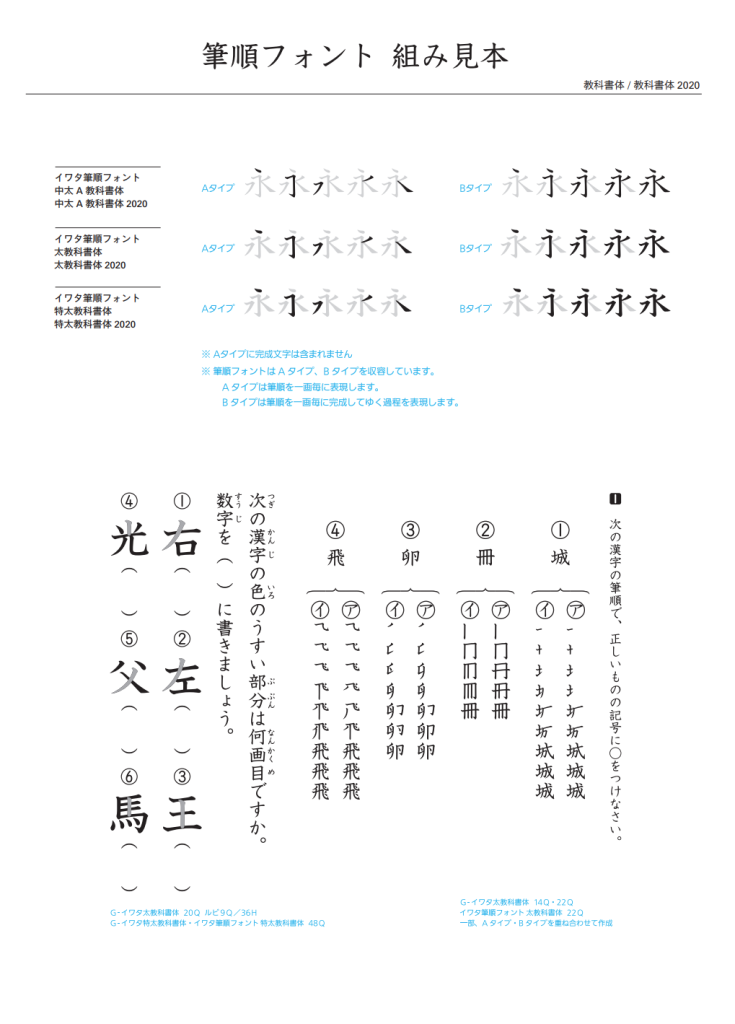
筆順フォント 教科書体2020
イワタ筆順フォント 中太A教科書体2020 Aタイプ
イワタ筆順フォント 中太A教科書体2020 Bタイプ
イワタ筆順フォント 太教科書体2020 Aタイプ
イワタ筆順フォント 太教科書体2020 Bタイプ
イワタ筆順フォント 特太教科書体2020 Aタイプ
イワタ筆順フォント 特太教科書体2020 Bタイプ
「イワタ筆順フォントは、文字の正しい画数や筆順(筆の入り、押さえ、ハネ、トメ)が、一目でわかりやすい形状で制作されたフォントです。 筆順フォントは2つのタイプを収容しています。」
・Aタイプは筆順を一画毎に表現します。
・Bタイプは筆順を一画毎に完成してゆく過程を表現します。
2020年度から小学校学習指導要領により、国語の学年別漢字配当表の変更が実施されます。
「イワタ筆順フォント 新教科書体」「イワタ筆順フォント 教科書体2020」はこの変更内容に合わせた漢字配当で収容しています。